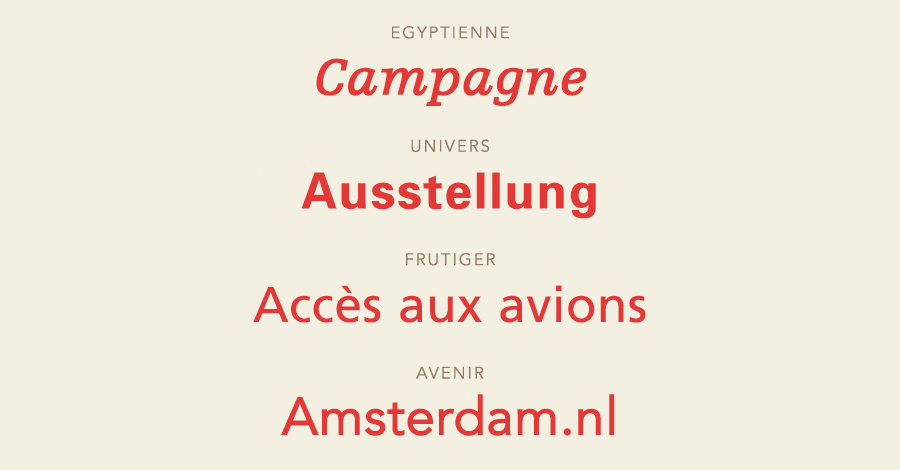
Adrian Frutiger gestorben: Erinnerungen an seine berühmte Schriften-Familie
Schriften des verstorbenen Typografen Adrian Frutiger
Am vergangenen Samstag ist der berühmte Typograf Adrian Frutiger im Alter von 87 Jahren verstorben. In seiner langen Karriere hatte er unter anderem die „Univers“ und die „Frutiger“ entworfen. Vor allem mit der Frutiger verknüpfe ich schöne Erinnerungen, begleitet sie mich doch bereits seit meiner Ausbildung als Schriftsetzer. Damals hatte ich einen Gesellen als Ausbilder, der großer Fan von der Frutiger war. Statt auf die Helvetica zu setzen (die wirklich jeder hatte), schickte er mich immer los, um die Setzkästen der Frutiger-Schrift zu holen. Ulkig: Mein Ausbilder hatte einen dezenten Sprachfehler, weshalb ich lange Zeit dachte, die korrekte Aussprache der Schrift laute „Fruchtiger“. Heute erzähle ich diese Anekdote gerne den Teilnehmern meines Bleisatz-Workshops – und kann ihnen die Schrift sogar als Bleilettern zeigen.
Frutiger zur Orientierung
Später hatte ich mit der Frutiger viel zu tun, weil wir in meiner Werbeagentur viele Verlagskunden betreuten. In den 90er-Jahren verwendete fast jeder Verlag die Frutiger als Hausschrift – kein Wunder: Sie ist eine sehr elegante und besonders gut lesbare Schrift, die sich von der Helvetica deutlich abhebt. Deshalb ist sie auch sehr beliebt, wenn es darum geht, Orientierungssysteme zu beschriften, zum Beispiel an Flughäfen.
Zeitlose Schriftenfamilie
Als Typograph finde ich sehr bemerkenswert, dass die Frutiger in ihrem Schnitt recht groß wirkt im Vergleich zu anderen Linear-Antiqua-Schriften. Aus diesem Grund kann man sie im Fließtext auch getrost einen Punkt kleiner setzen als beispielsweise eine Univers oder Helvetica. Ich verwende sie nach wie vor sehr gerne – sie ist ein echtes Arbeitspferd, mit der man nichts falsch machen kann.
Ein Typograf aus Leidenschaft
Mit dem Tod von Adrian Frutiger verliert die Welt einen ihrer bewunderten Typografen. Mein aufrichtiges Beileid gilt seiner Familie, seinen Freunden und Bekannten. Adrian Frutiger wird, das ist gewiss, in seinen Schriften und Werken immer weiterleben.